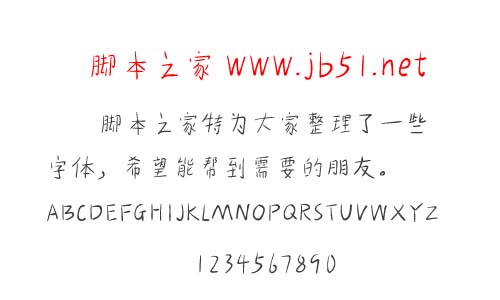
墨八歲體字體可以作為手機(jī)字體使用,是一款較常見用于簽名設(shè)計(jì)方面的字體,其特色在于主要提供了Regular字體風(fēng)格樣式,適用于細(xì)體設(shè)計(jì)字體、創(chuàng)意設(shè)計(jì)字體、手寫設(shè)計(jì)字體、簽名設(shè)計(jì)字體,歡迎有需要或喜歡此字體的朋友們前來下載使用。